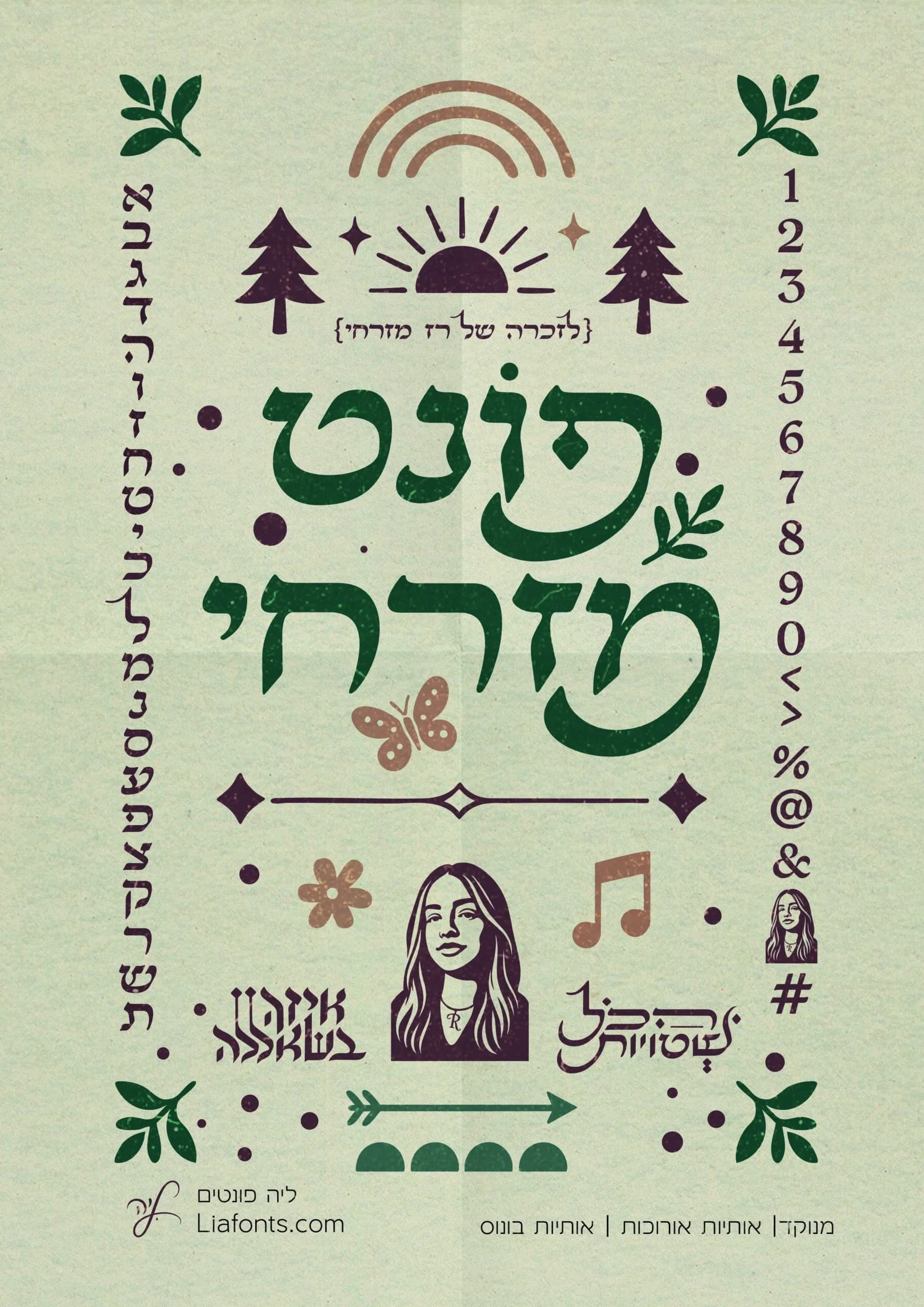
אותיות עם נשמה מזרחית וזיכרון שלא יישכח. פונט מזרחי נולד מתוך עיצובים לזכרה של רז-מזרחי ז״ל, שנרצחה במסיבת נובה באוקטובר 2023. אביה של רז פנה אליי וביקש שאעצב את המשפטים שרז הייתה אומרת ואיפיינו אותה מאוד הכל שטויות איזה בשאללה מתוך זה נוצר פונט שלם – אות אחרי אות – שמספר קצת מהסיפור שלה. פונט מזרחי הוא פונט עברי קליגרפי בסגנון מזרחי־אורגני, עם אותיות: מוקפדות, חדות אך חמות, עם קונטרסט עבה־דק ונוכחות טיפוגרפית מלאה. הוא שואב השראה מעולם המזרח, שפת רחוב רכה ומדויקת, ואסתטיקה של כאב שהפך לאמנות. למה הוא מתאים? עיצובי פוסטרים, כותרות, ספרים, עטיפות ומיתוגים עם עומק עיצוב פואמות, תקליטים, קולנוע, מחול, פרויקטים אישיים ורגשיים מיזמים חברתיים שמבקשים נוכחות עיצובית עם משמעות. אריזות מזון בסגנון מזרחי, לוגואים ומיתוגים. תוספות ייחודיות בפונט: ליגטורות נבחרות מבית היוצר של רז: הכל שטויות איזה בשאללה רז רזי אייקון גרפי מעוצב המבוסס על דמותה של רז רז מזרחי. משפטים בעיצוב ידני שניתן להשתמש בהם כטקסט חי